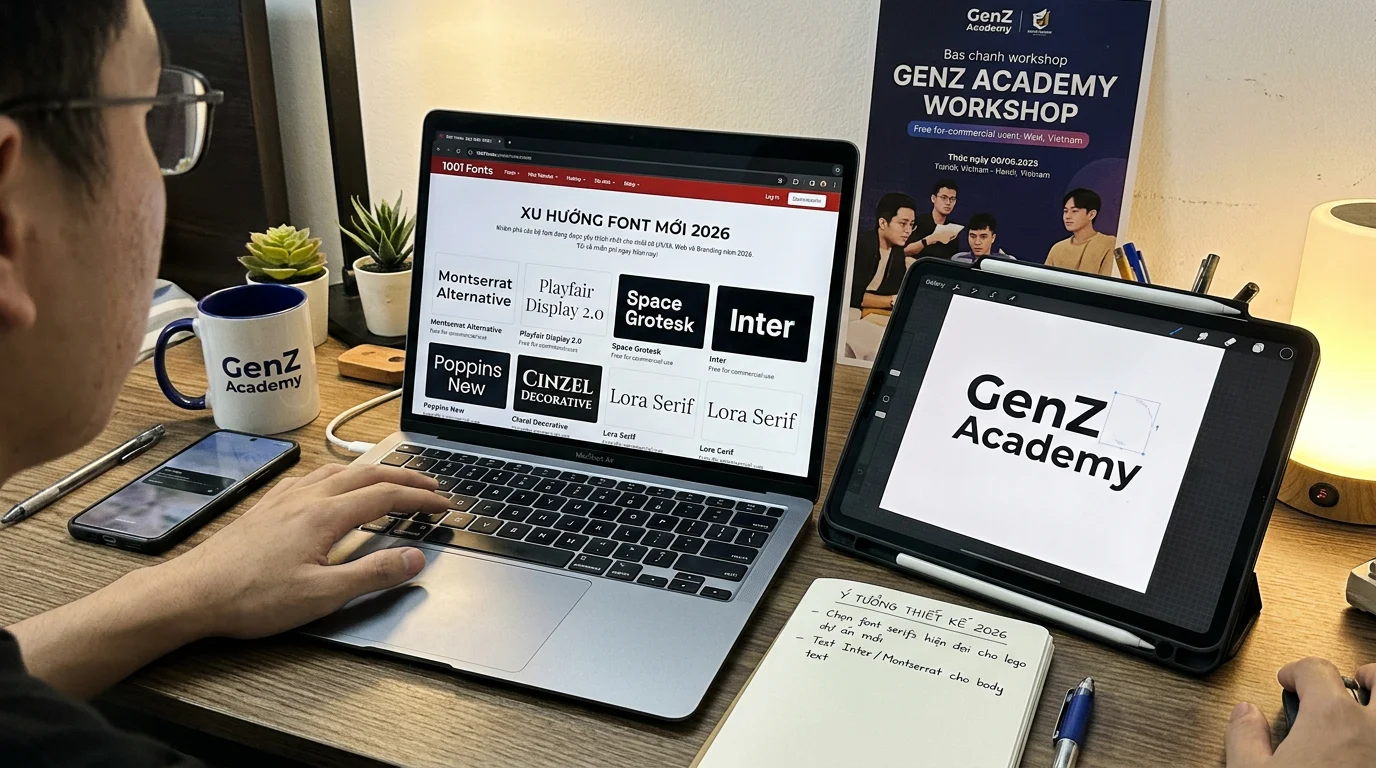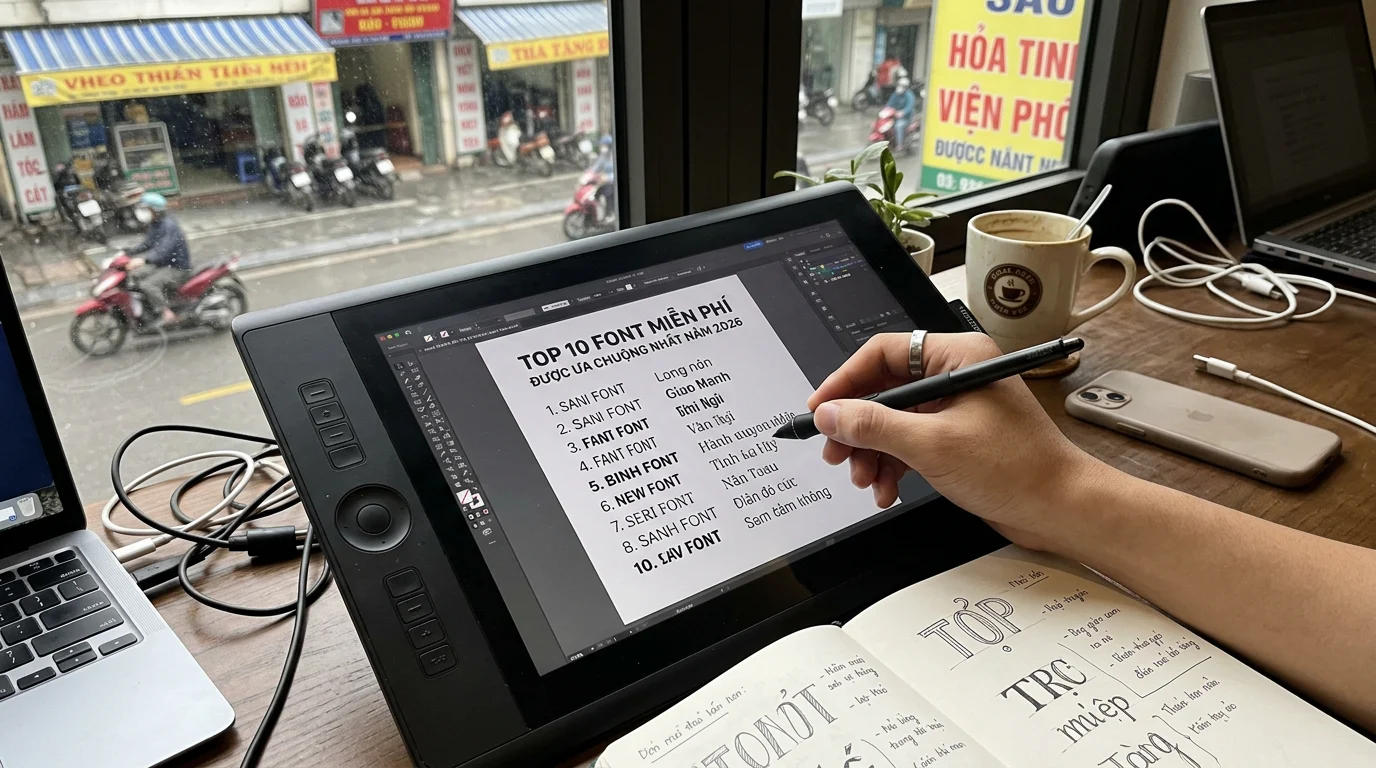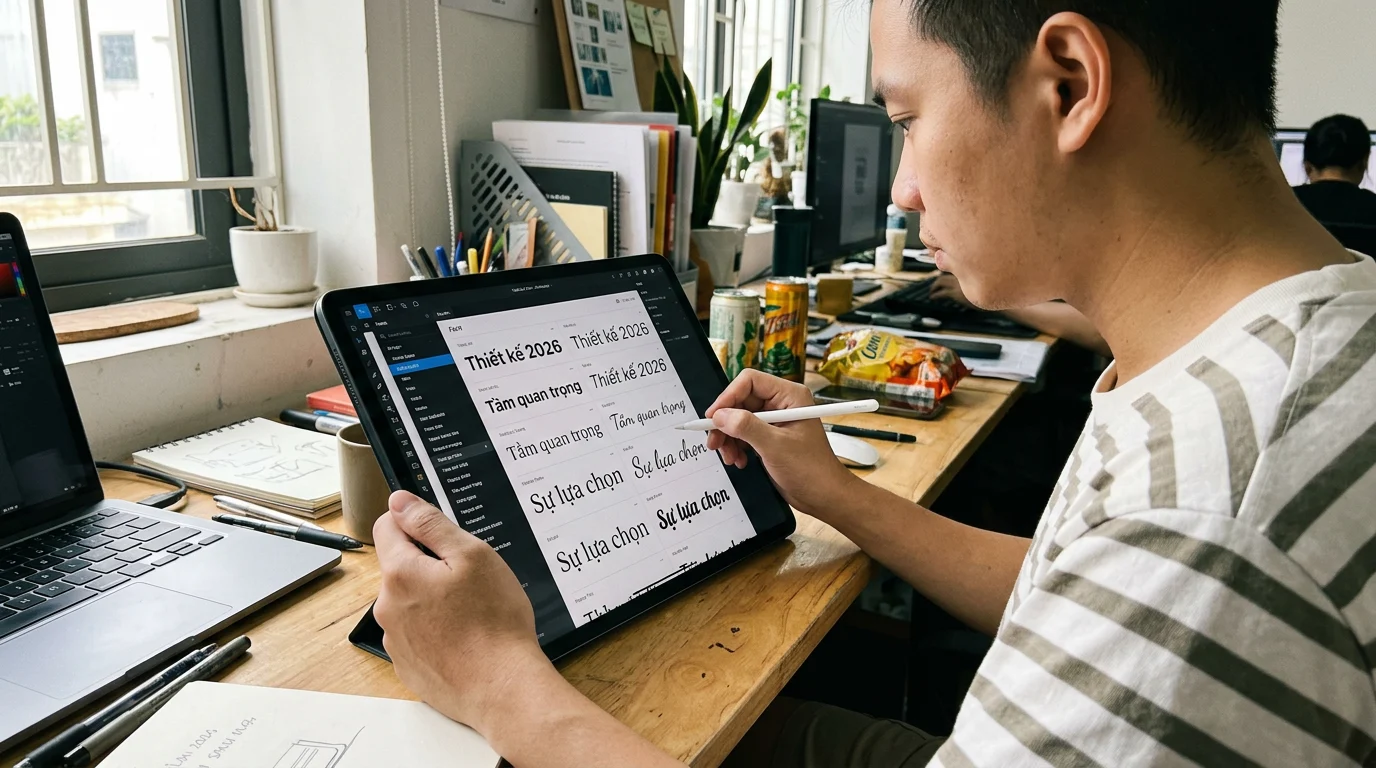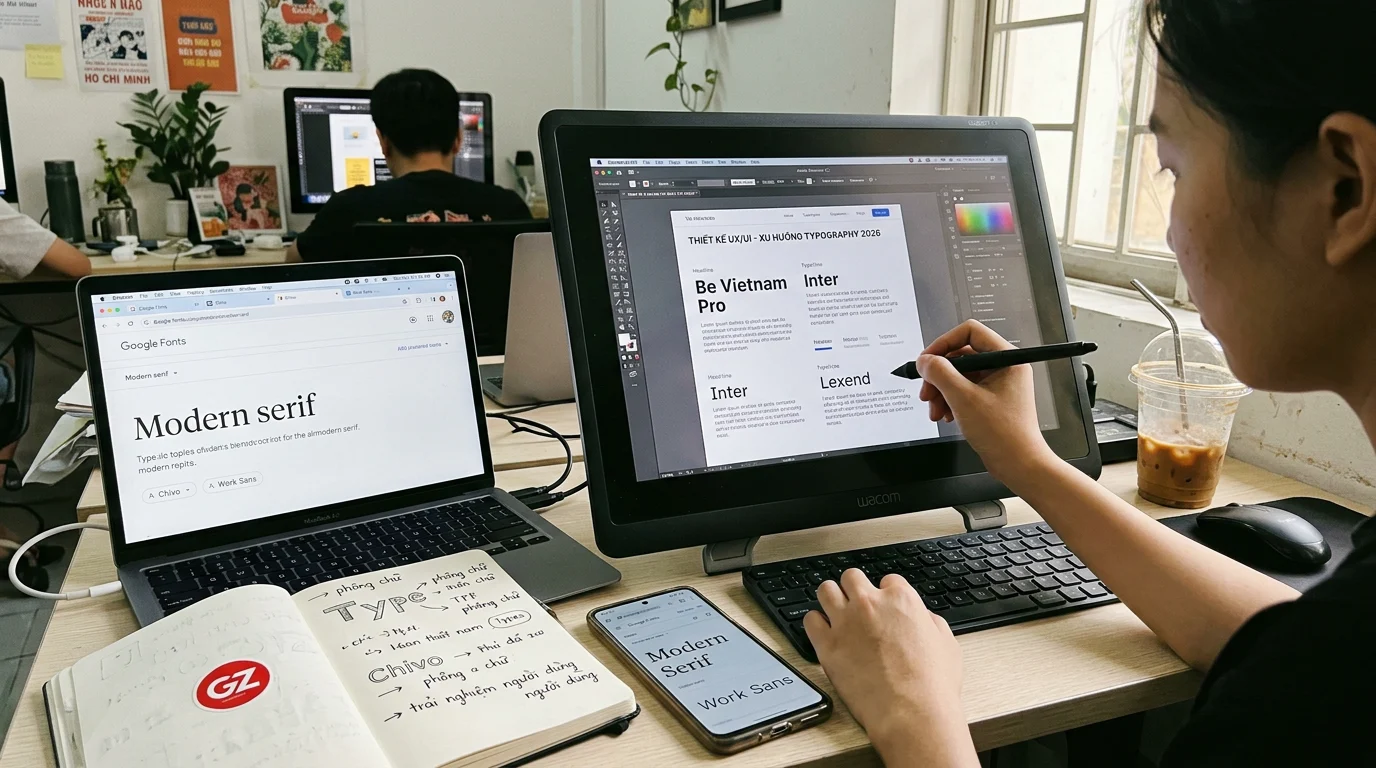
Top 10 loại font miễn phí được sử dụng nhiều nhất năm 2026
Trong năm 2026, việc lựa chọn kiểu chữ phù hợp không chỉ dừng lại ở tính thẩm mỹ mà còn là yếu tố then chốt quyết định trải nghiệm người dùng. Các nhà thiết kế hiện nay đang ưu tiên những bộ font miễn phí chất lượng cao để tối ưu hóa hiệu suất hiển thị trên đa nền tảng. Dưới đây là bảng so sánh các nguồn cung cấp font uy tín nhất hiện nay:
Để khai thác hiệu quả 10 loại font miễn phí được sử dụng nhiều năm 2026, bạn cần lưu ý các điểm sau:
Việc sử dụng các nguồn tài nguyên uy tín như Google Fonts hay Font Squirrel giúp bạn tránh được rủi ro về bản quyền và đảm bảo tính chuyên nghiệp cho sản phẩm. Hãy bắt đầu bằng việc xây dựng một thư viện font cá nhân chất lượng, kết hợp tối đa 2-3 kiểu chữ trong một thiết kế để tạo sự cân bằng và thu hút thị giác tối ưu nhất cho người xem.
Khám phá bộ sưu tập 10 loại font miễn phí được sử dụng nhiều nhất năm 2026 giúp nâng tầm thiết kế của bạn.
Góc làm việc sáng tạo với các bộ font chữ miễn phí được ưa chuộng nhất năm 2026, hỗ trợ tối ưu cho các dự án thiết kế chuyên nghiệp.
1. Tầm quan trọng của việc lựa chọn font chữ trong thiết kế năm 2026
Trong bối cảnh thiết kế kỹ thuật số năm 2026, typography không chỉ đơn thuần là công cụ truyền tải nội dung mà còn là yếu tố cốt lõi định hình trải nghiệm người dùng (UX). Việc lựa chọn font chữ phù hợp giúp thương hiệu tạo ra dấu ấn thị giác mạnh mẽ, tăng khả năng đọc hiểu và dẫn dắt cảm xúc của khách hàng ngay từ cái nhìn đầu tiên. Khi xu hướng thiết kế tối giản và hiện đại lên ngôi, các nhà thiết kế ngày càng khắt khe hơn trong việc tìm kiếm những bộ font vừa đảm bảo tính thẩm mỹ, vừa tối ưu hóa khả năng hiển thị trên đa nền tảng.
Việc ưu tiên sử dụng các font chữ miễn phí chất lượng cao mang lại lợi thế lớn về chi phí mà vẫn đảm bảo tính chuyên nghiệp cho các dự án sáng tạo. Dưới đây là bảng so sánh các đặc điểm chính của việc lựa chọn font chữ trong năm 2026:
Để tối ưu hóa quy trình làm việc, các designer cần lưu ý những điểm sau:
- Ưu tiên các font có hỗ trợ đầy đủ bộ ký tự tiếng Việt để tránh lỗi hiển thị khi trình bày văn bản.
- Thử nghiệm khả năng hiển thị của font trên các thiết bị di động và màn hình có độ phân giải cao.
Việc lựa chọn đúng font chữ không chỉ giúp nâng tầm thẩm mỹ cho ấn phẩm mà còn là cách thông minh để tối ưu hóa ngân sách thiết kế. Bằng cách tận dụng các nguồn tài nguyên uy tín, bạn có thể dễ dàng tìm thấy những bộ font chất lượng, giúp thông điệp của thương hiệu trở nên sắc nét và chuyên nghiệp hơn trong mắt người dùng. Hãy luôn đặt trải nghiệm người đọc làm trọng tâm khi đưa ra quyết định lựa chọn kiểu chữ cho bất kỳ dự án nào.
Việc lựa chọn font chữ phù hợp là yếu tố then chốt giúp nâng tầm thẩm mỹ và truyền tải thông điệp hiệu quả trong các dự án thiết kế năm 2026.
Xu hướng typography hiện đại và trải nghiệm người dùng
Trong năm 2026, typography không chỉ đơn thuần là công cụ truyền tải nội dung mà đã trở thành yếu tố cốt lõi định hình trải nghiệm người dùng (UX). Một bộ font được lựa chọn tinh tế có khả năng dẫn dắt thị giác, tạo cảm xúc và tăng cường khả năng đọc hiểu trên mọi thiết bị. Khi người dùng ngày càng ưu tiên sự tối giản và tốc độ tải trang, việc sử dụng các font chữ miễn phí chất lượng cao trở thành giải pháp tối ưu giúp designer cân bằng giữa tính thẩm mỹ và hiệu suất kỹ thuật.
Việc lựa chọn font chữ phù hợp giúp thương hiệu tạo ra sự khác biệt trong môi trường số cạnh tranh. Dưới đây là bảng so sánh các đặc điểm chính của các nhóm font phổ biến hiện nay:
| Loại Font | Đặc điểm chính | Ứng dụng phổ biến |
|---|---|---|
| Sans-Serif | Hiện đại, dễ đọc | Giao diện web, ứng dụng |
| Serif | Cổ điển, sang trọng | Tiêu đề, ấn phẩm in ấn |
| Display | Độc đáo, nghệ thuật | Logo, nhận diện thương hiệu |
Để đạt được hiệu quả thiết kế tối ưu, các chuyên gia thường tuân thủ những nguyên tắc sau:
- Ưu tiên các font có khả năng hiển thị tốt trên màn hình độ phân giải cao.
- Hạn chế sử dụng quá nhiều kiểu chữ khác nhau trong cùng một bố cục để tránh gây nhiễu thị giác.